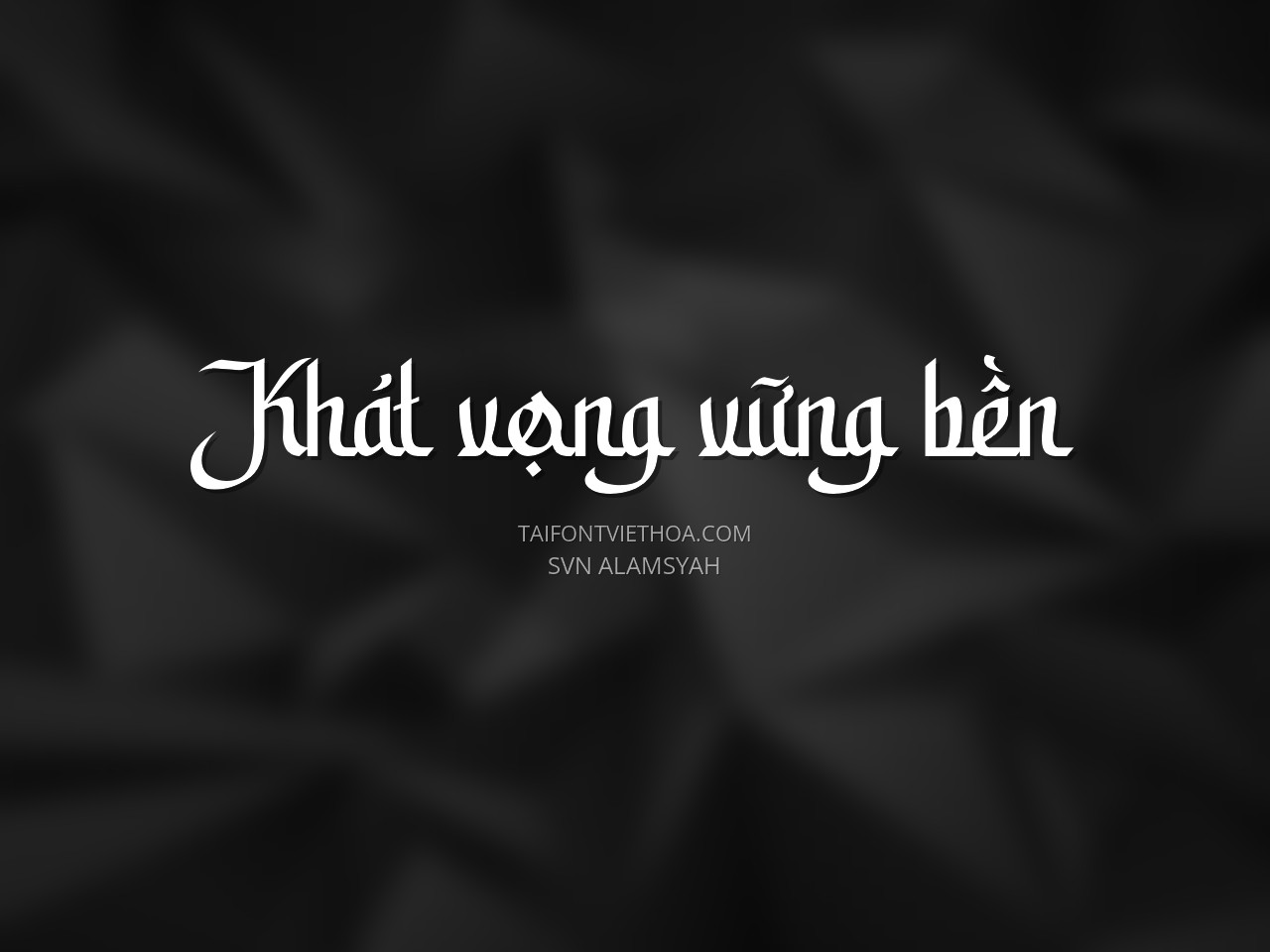
Font việt hóa SVN Alamsyah
Tác giả Font: Kong Font
Giới thiệu về font SVN Alamsyah – Kiểu chữ handwritten độc đáo, mềm mại và cá tính
SVN Alamsyah là phiên bản Việt hóa của font Alamsyah – một kiểu chữ handwritten mang phong cách độc đáo, mềm mại và rất cá tính. Font được thiết kế với các nét chữ tự nhiên, uyển chuyển và biểu cảm, tạo cảm giác gần gũi và sáng tạo, rất phù hợp cho các dự án thiết kế thiệp, poster, thương hiệu cá nhân và truyền thông mạng xã hội.
Phiên bản Việt hóa của SVN Alamsyah đã được Taifontviethoa.comchăm sóc kỹ lưỡng, hỗ trợ đầy đủ dấu tiếng Việt cùng hơn 60 ngôn ngữ khác. Font giúp các nhà thiết kế dễ dàng áp dụng trong nhiều dự án sáng tạo mà vẫn giữ được phong cách trẻ trung, thân thiện và độc đáo.
Thiết kế viết tay biểu cảm – Lý tưởng cho thiết kế sáng tạo và thương hiệu cá nhân
SVN Alamsyah sở hữu các nét chữ mềm mại, uyển chuyển với đường nét tự nhiên và tinh tế, tạo nên sự hài hòa và thu hút trong tổng thể thiết kế. Font rất phù hợp cho tiêu đề, logo, thiệp mời, bao bì sản phẩm và các phần thiết kế cần điểm nhấn cá tính và gần gũi.
Ứng dụng lý tưởng: thiết kế thiệp, poster, logo thương hiệu cá nhân, bao bì mỹ phẩm, bài đăng mạng xã hội và các dự án sáng tạo cần phong cách mềm mại, độc đáo. Ngành nghề phù hợp: truyền thông, mỹ phẩm, thời trang, nghệ thuật và các thương hiệu định vị theo phong cách trẻ trung, sáng tạo.